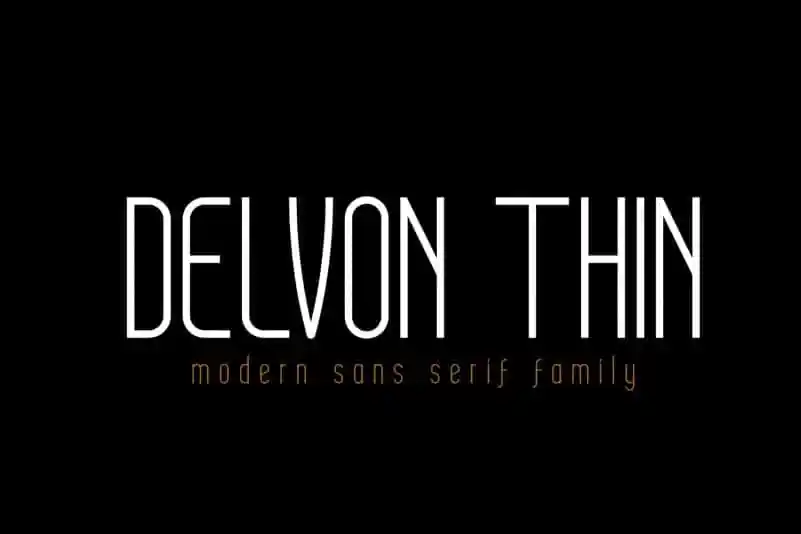
A fonte Delvon Sans Serif é uma família moderna de tipo grego que oferece um visual clean e limpo, perfeito para criar qualquer tipo de material visual – desde logotipos e rótulos até a capa de livros e materiais publicitários. Suave e profissional, ela não só se destaca em aplicativos como cartas de convite ou camisas de tênis, mas também tem uma elegância que complementará revistas e materiais de merchandising de alta qualidade. Seja você criando um novo projeto do zero ou imprimindo na cor para uma empresa sofisticada, Delvon Sans Serif oferece a perfeição de linhas retas e design limpo necessários para qualquer layout. Com sua funcionalidade versátil e estilo contemporâneo, Delvon Sans Serif é o tipo certo quando você precisa de um visual moderno que transmita confiança e eficiência.